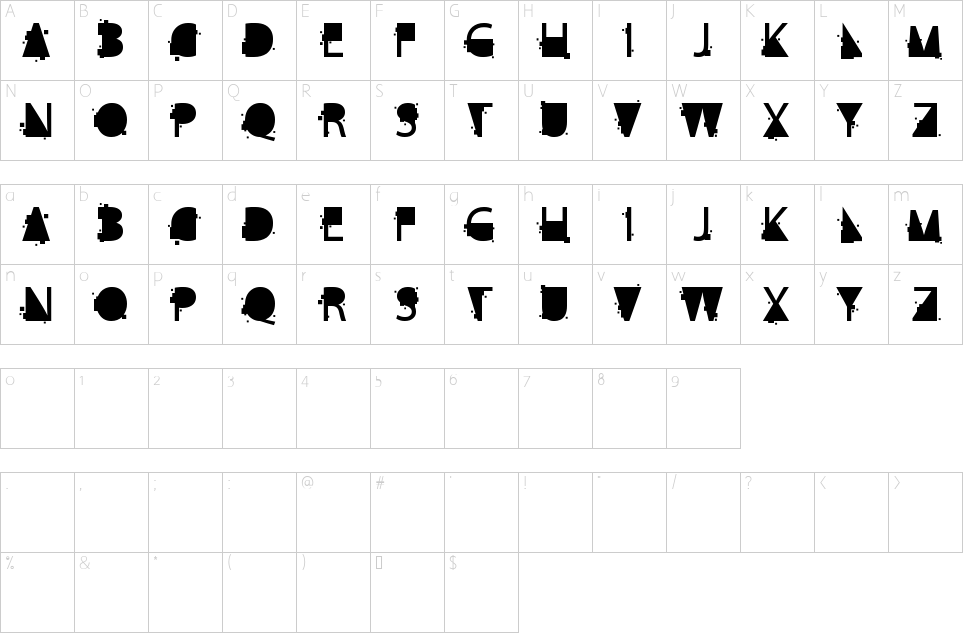
Cube Kila é uma elegante fonte gráfica que adiciona um toque moderno a seu design. Desenvolvida pelo designer desconhecido Qkila, a fonte é ideal para quem procura uma solução de texto minimalista e sofisticada. Suportando tanto o sistema Windows quanto o Mac, a fonte pode ser facilmente integrada em seu projeto. Download Cube Kila agora e faça seu design soar moderno e moderno. Com um design minimalista, a fonte é perfeita para aplicativos de design, materiais de marketing e qualquer projeto onde um estilo moderno é desejado. Com apenas 1,461 downloads, você está garantindo que é um fonte que combina perfeitamente com a sua visão.